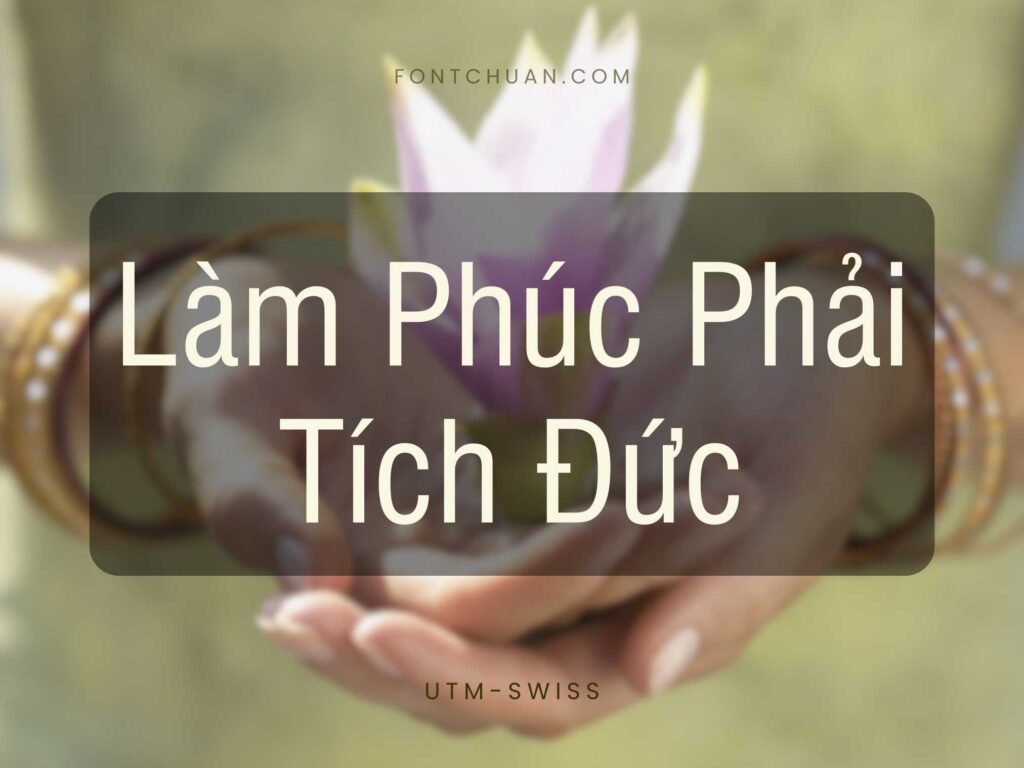
UTM Swiss là một font chữ sans-serif hiện đại, được phát triển bởi Công ty TNHH Vitoen. Với thiết kế đơn giản, gọn gàng và dễ đọc, font này mang lại cảm giác chuyên nghiệp và tinh tế cho các dự án thiết kế. Đặc biệt, UTM Swiss đã được Việt hóa bởi Thiên Minh, đảm bảo hỗ trợ đầy đủ các dấu và ký tự tiếng Việt, giúp người dùng Việt Nam có trải nghiệm sử dụng hoàn hảo. Ngoài tiếng Việt, font này còn hỗ trợ nhiều ngôn ngữ khác, mở rộng khả năng ứng dụng trong các thiết kế quốc tế. Thành viên của Font Chuẩn đã sưu tầm và giới thiệu UTM Swiss đến cộng đồng thiết kế, giúp họ có thêm lựa chọn cho các dự án sáng tạo. Với sự kết hợp giữa tính thẩm mỹ và khả năng ứng dụng cao, font này không chỉ phù hợp cho các thiết kế tiêu đề, poster, ấn phẩm quảng cáo mà còn được xem là một lựa chọn lý tưởng khi sử dụng làm Font logo, mang lại vẻ đẹp hiện đại và sự chuyên nghiệp cho thương hiệu.
Với sự kết hợp giữa tính thẩm mỹ và khả năng ứng dụng cao, UTM Swiss phù hợp cho các thiết kế logo, tiêu đề, poster và các ấn phẩm quảng cáo khác. Ngoài ra, khi làm Font sinh nhật, UTM Swiss còn là lựa chọn lý tưởng cho các thiết kế thiệp mừng sinh nhật, banner và poster sự kiện, mang đến không khí vui tươi, hiện đại nhưng vẫn giữ được sự tinh tế cho sản phẩm thiết kế.